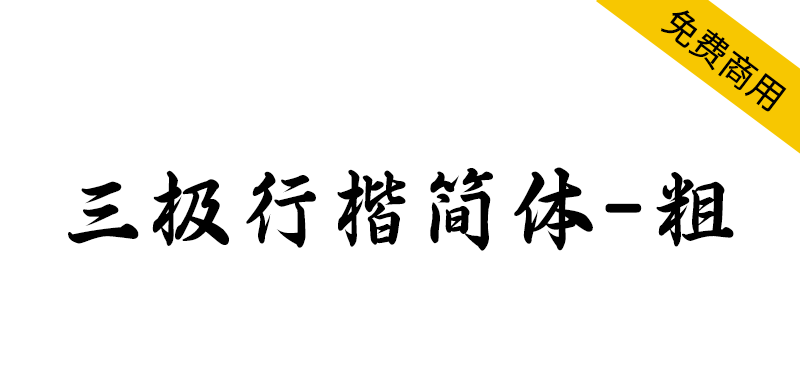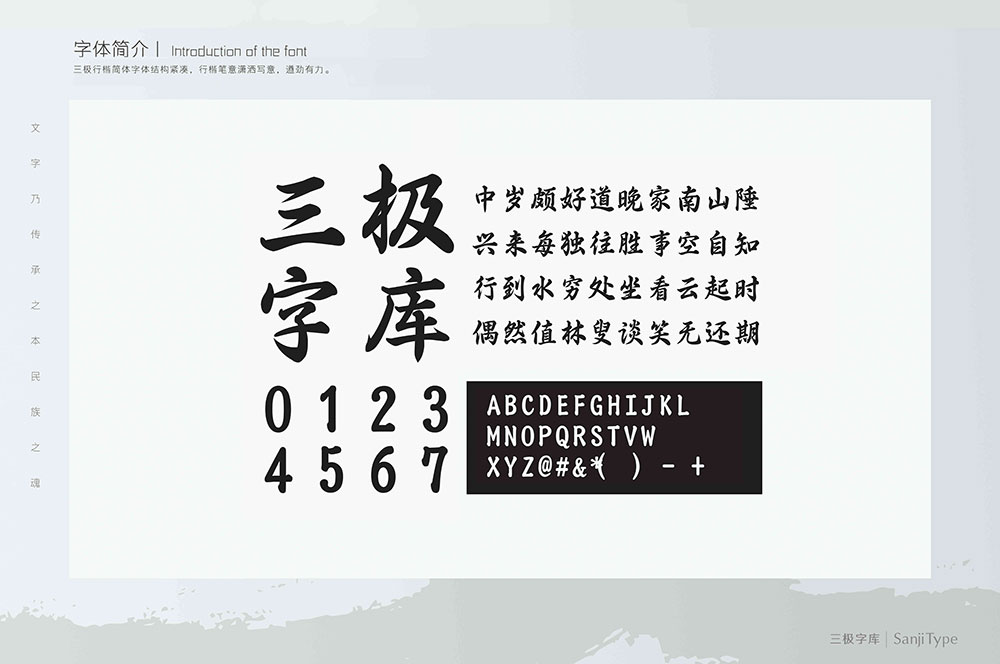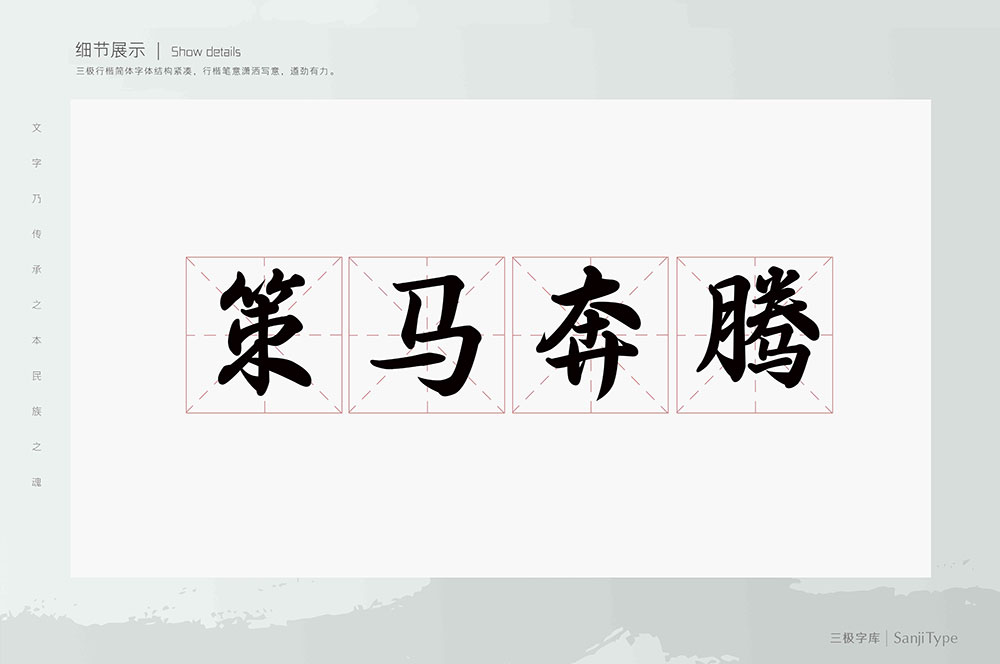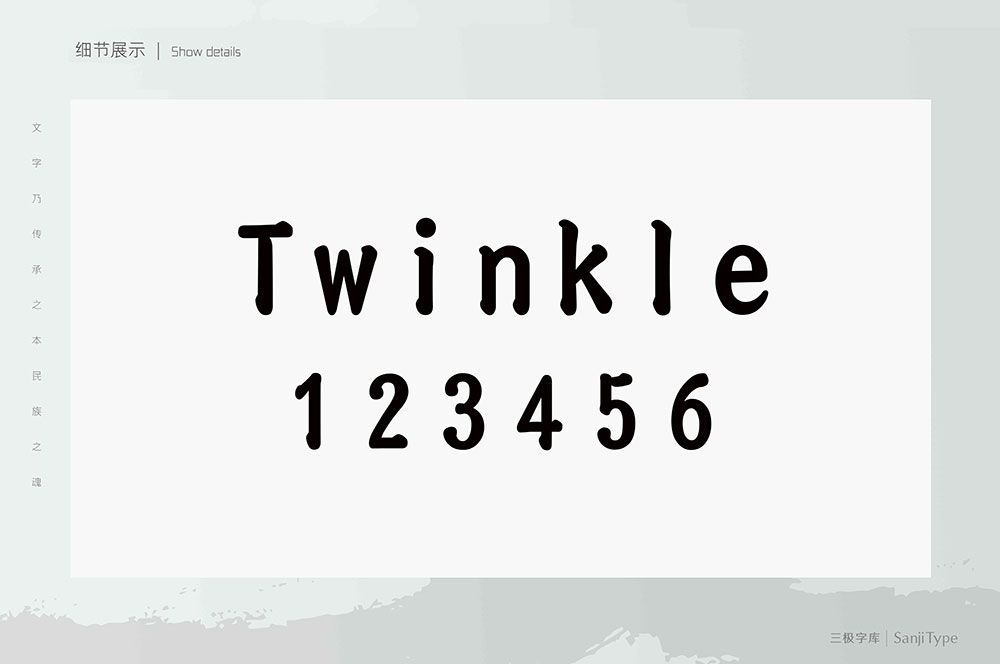
【三极行楷简体-粗】结构紧凑,行楷笔意潇洒写意,遒劲有力
三极行楷简体,是一款免费商用的行楷字体。字体结构紧凑,笔画潇洒写意,遒劲有力,大气隆重。适用于国潮经典、传统节日的主题排版,以及商业类品牌的广告设计、媒体标题以及社交网络个性化用字。
【三极行楷简体-粗】结构紧凑,行楷笔意潇洒写意,遒劲有力